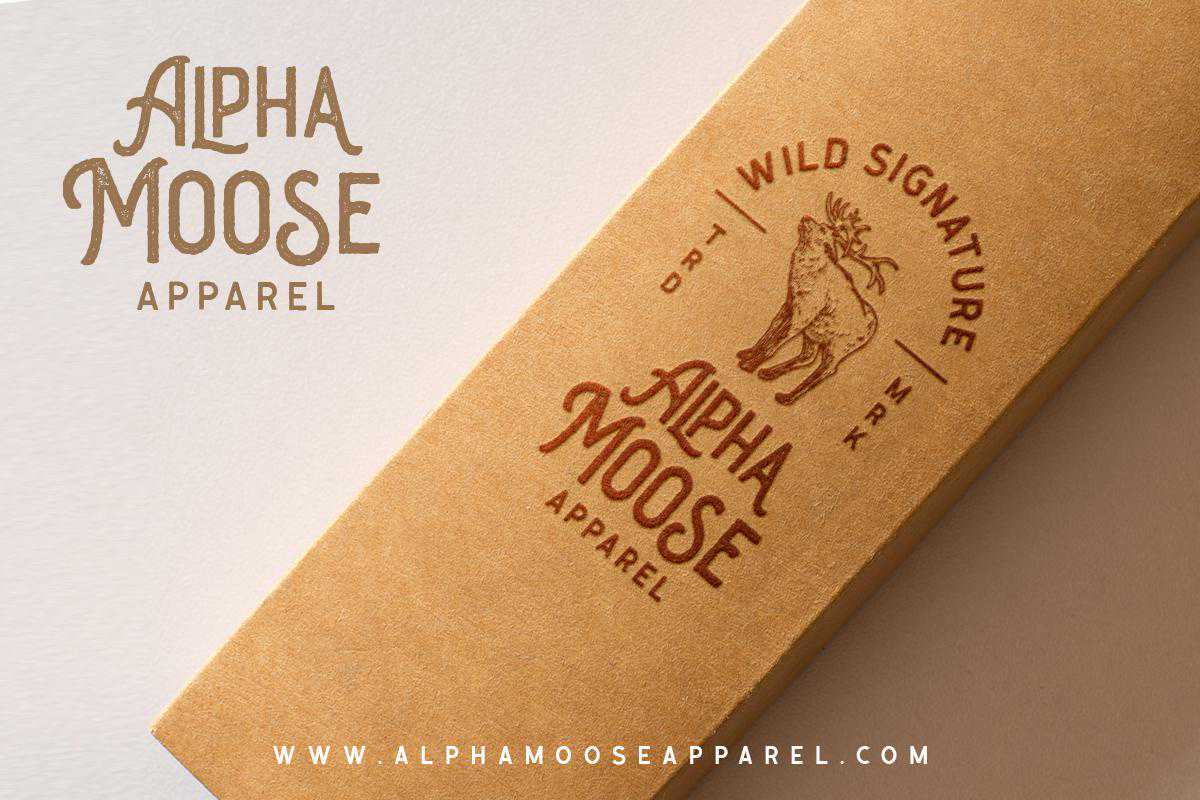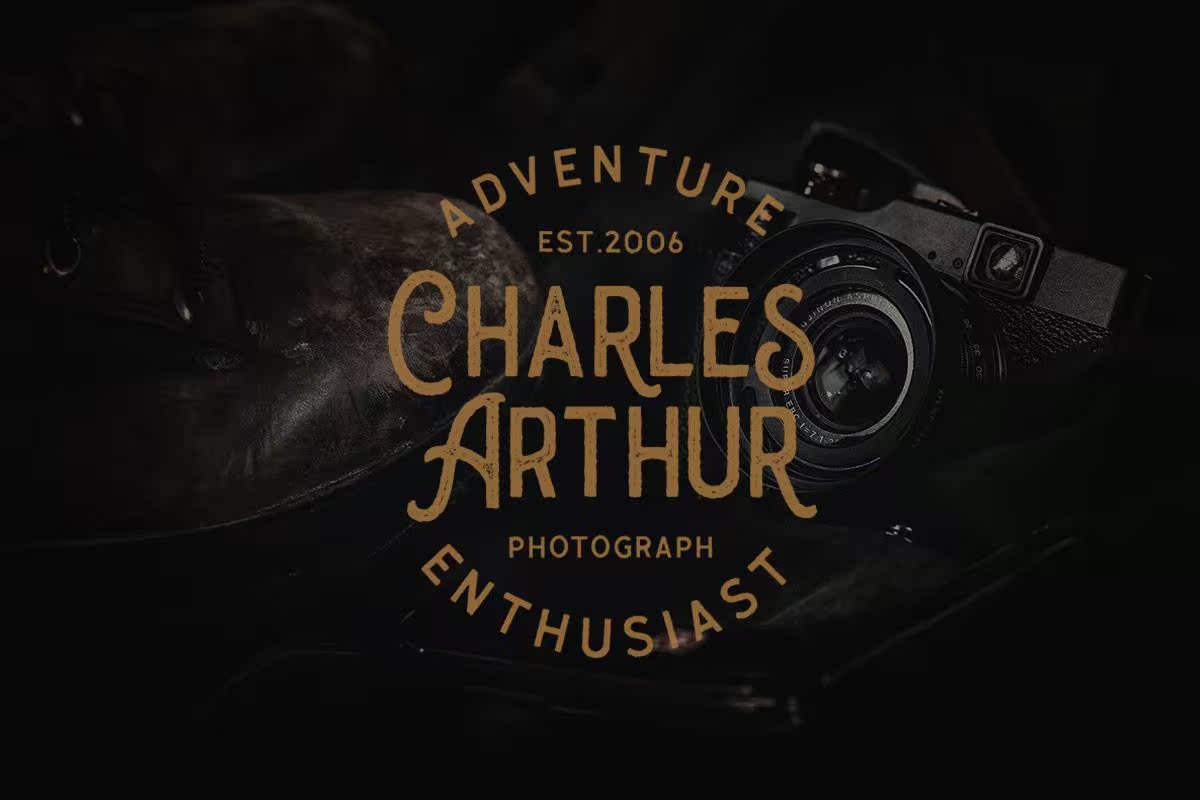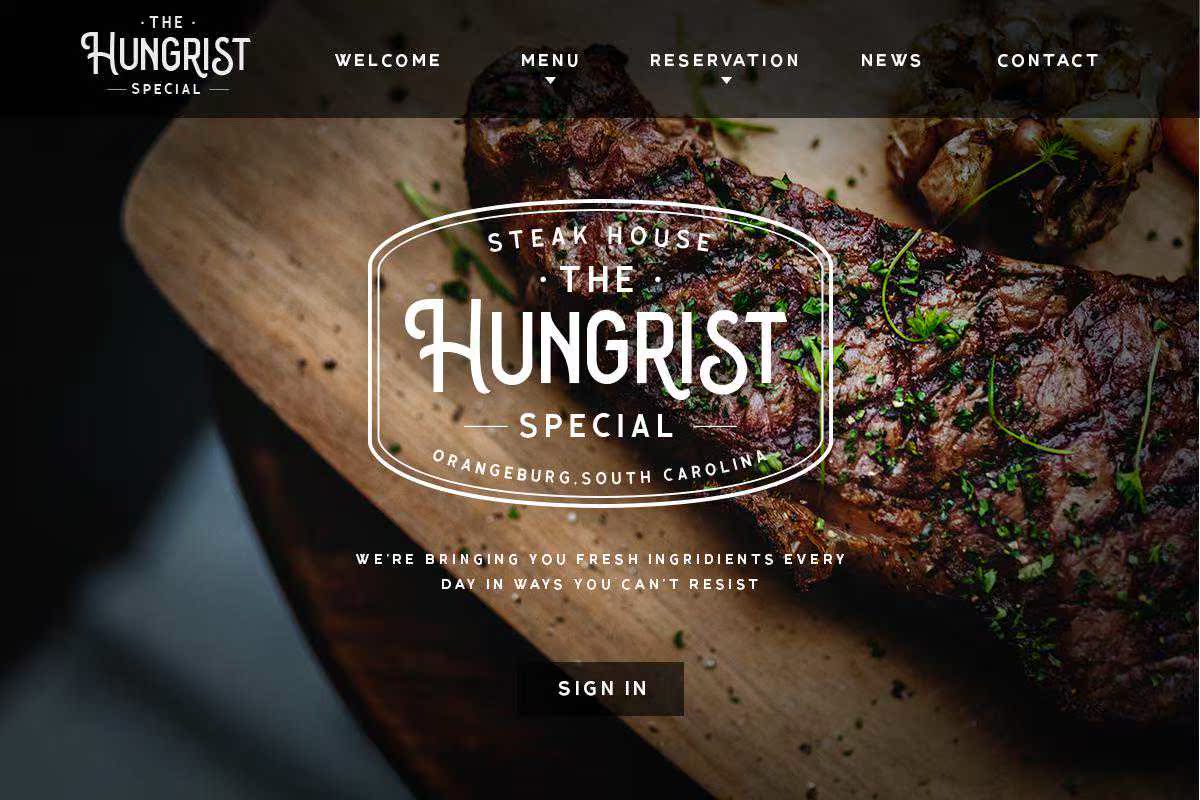
goldies是一个显示字体系列,适合需要字体的用户,用于标题、标识、服装、邀请、品牌、包装、广告等。此字体包括大写、小写、标点符号、符号和数字、样式设置、替换、连字、,ETCALSO支持多语言和可读性UAEncoded。Goldies是一个显示字体系列,适用于需要标题、标识、服装、邀请、品牌、包装、广告等字体的用户。此字体包括大写、小写、标点符号、符号和数字、文体设置替换、连字等,支持多语言和可读性UAEncoded。